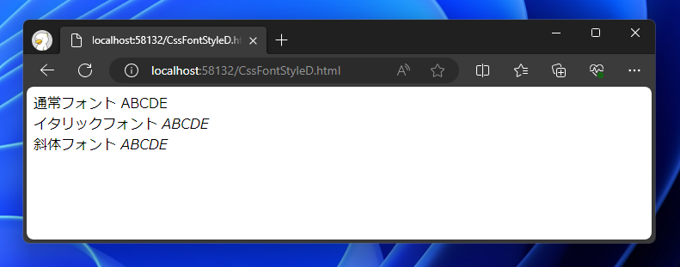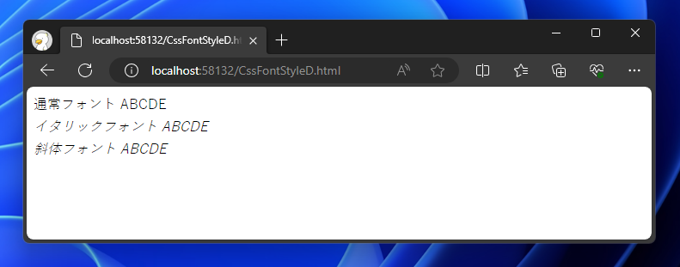
font-styleプロパティを設定してもマルチバイト文字 (日本語文字) が斜体で表示されない
font-styleプロパティを設定してもマルチバイト文字 (日本語文字) が斜体で表示されない現象と対処法の紹介です。
現象の確認
font-styleプロパティを設定してもマルチバイト文字 (日本語文字) が斜体で表示されない場合があります。
以下のHTML、CSSファイルを作成します。
Windows 10/11 のWebブラウザで上記HTMLファイルを表示します。
font-sytleでitalicやobliqueが設定されていますが、日本語の文字列が斜体表示されません。
font-styleプロパティを設定してもマルチバイト文字 (日本語文字) が斜体で表示されない:画像1
原因
WindowsのWebブラウザでデフォルトで表示される「メイリオ」に斜体のフォントが無いためです。
対処法
斜体のあるフォント「MSゴシック」「MS明朝」「游ゴシック」を設定します。
CSSファイルを変更します。フォントを「游ゴシック」に設定しています。
変更後、WebブラウザでHTMLファイルを表示します。 下図のページが表示されます。游ゴシックで描画されるため、日本語文字列が斜体で表示されました。
font-styleプロパティを設定してもマルチバイト文字 (日本語文字) が斜体で表示されない:画像2